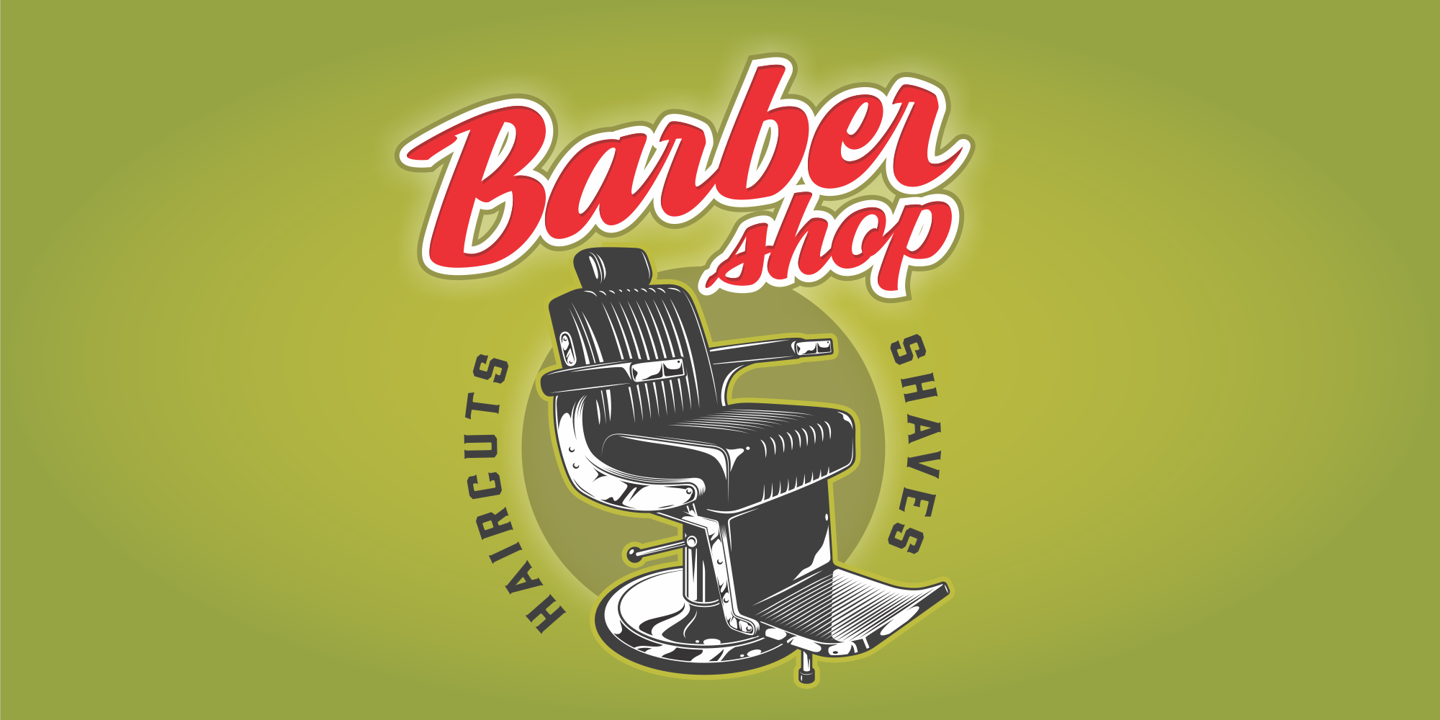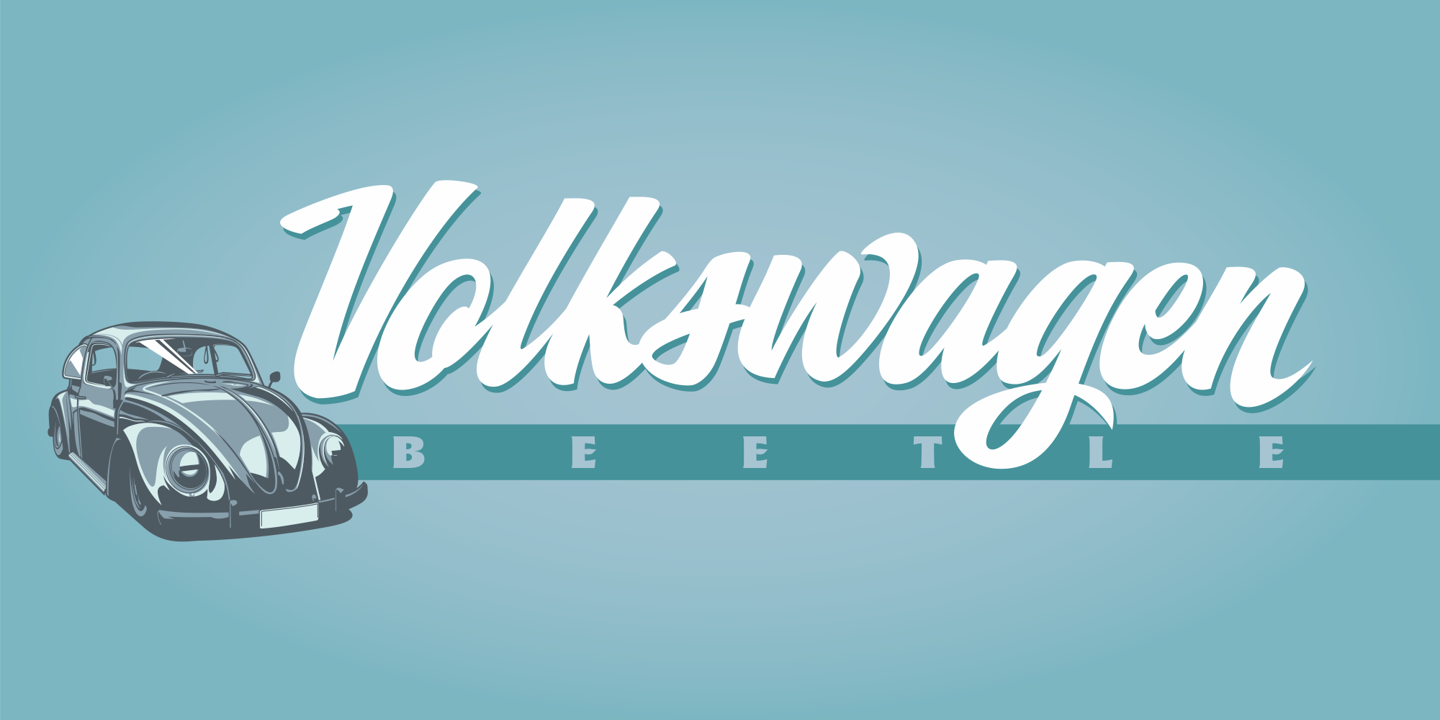
Aplin Script Font
Description de Aplin Script Font
Cette écriture italique manuscrite est une autre police polyvalente produite par Jeff Marshall. Nommé en l’honneur de feu Ron Aplin, qui a encadré Jeff en tant qu’apprenti écrivain d’enseignes au début de sa carrière. Cette police comprend 19 ligatures uniques et 15 glyphes de fin spéciaux alternatifs.